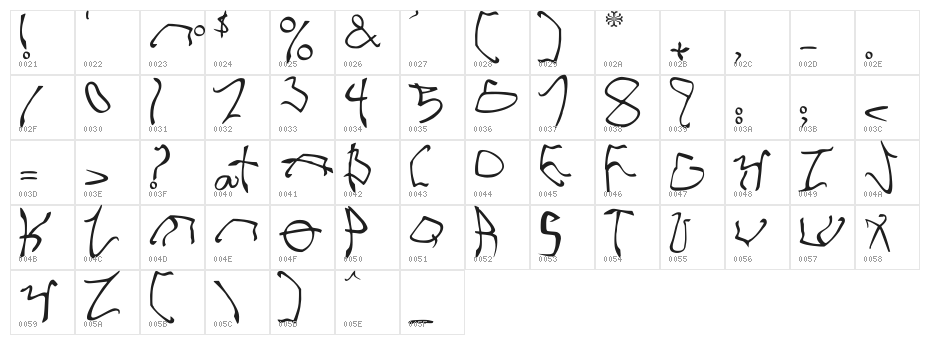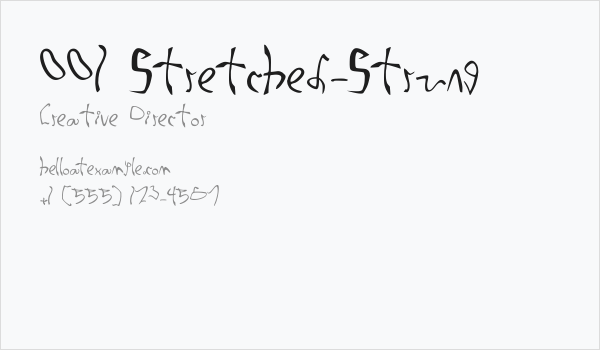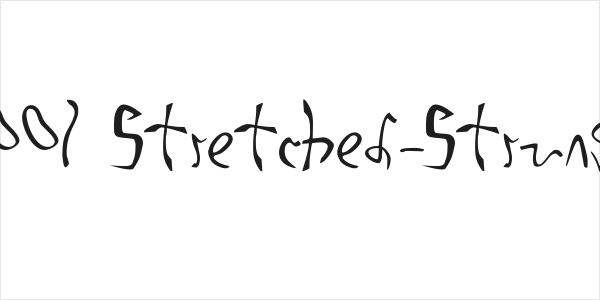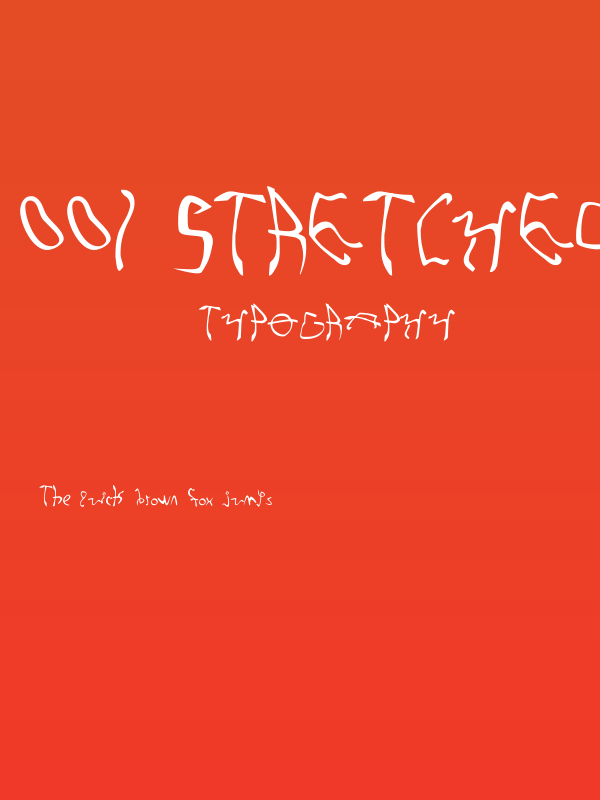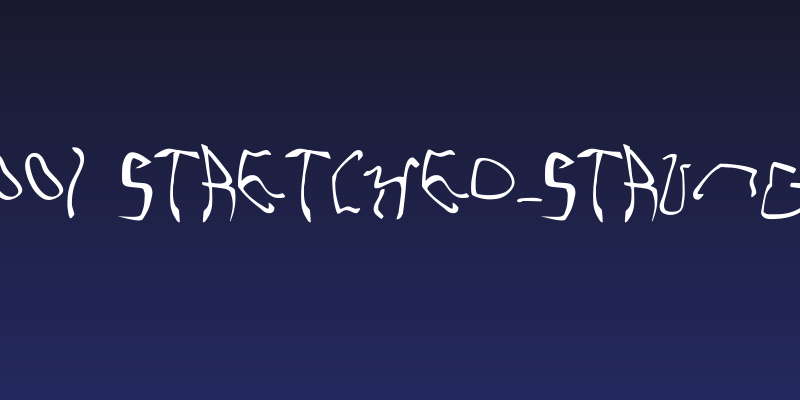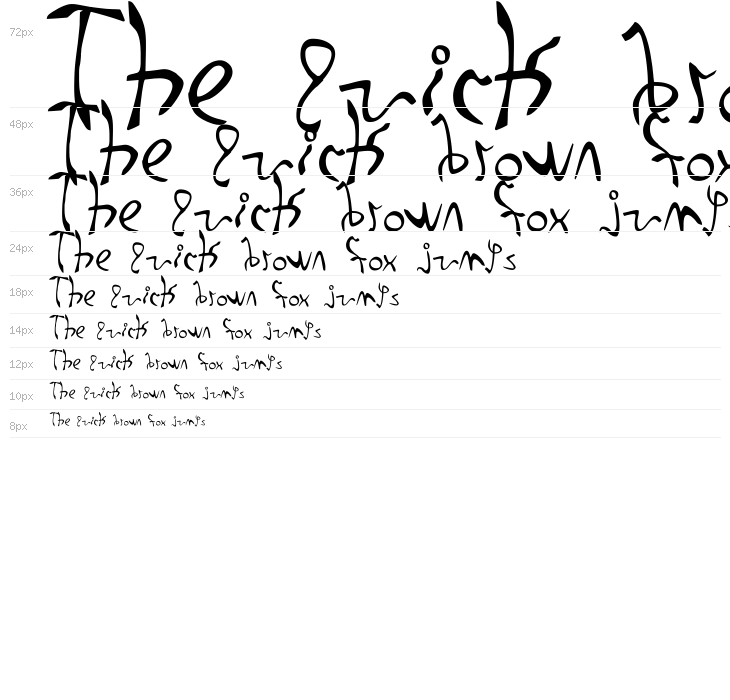
001 Stretched-Strung Font
| 名前 | 001 Stretched-Strung |
| カテゴリ | Graffiti |
| 幅 | Expanded |
| 全体的なスタイル | Artistic |
| 用途 | Logos, Posters, Artistic Branding |
| おすすめプロジェクト | Ideal for creative projects such as album covers, posters, and artistic branding where a unique and expressive typeface is desired. |